社群媒體五大最佳草寫字體
在視覺主導的社群媒體世界中,脫穎而出至關重要。雖然令人驚豔的圖片和影片至關重要,但您使用的文字也會顯著影響您的參與度和品牌形象。 哪種字體模仿草寫字跡,並能讓您的貼文更引人注目?使用獨特的 社群媒體字體,尤其是優雅的草寫風格,可以將您的內容從平凡轉變為迷人。這篇文章將揭示五種頂級草寫字體,所有這些字體都可以通過 草寫字體產生器 輕鬆取得,非常適合讓您的社群媒體形象真正引人注目。準備提升您的動態消息了嗎?立即探索我們的草寫字體產生器!
為什麼要在您的社群媒體上使用花俏的草寫字體?
在我們深入探討我們的最佳選擇之前,讓我們考慮一下 為什麼 您應該將 花俏的草寫字體 納入您的社群媒體策略。 時尚的文字如何使您的線上形象受益?
提升品牌個性
草寫字體可以立即為您的品牌注入個性。無論您追求的是優雅、俏皮還是藝術,合適的字體都能幫助傳達您的獨特聲音,並讓您與競爭對手區隔開來。這創造了更令人難忘的 社群媒體美學。
提升參與度和分享次數
引人注目的文字自然會吸引注意。當您的貼文具有視覺吸引力時,使用者更有可能停止捲動、閱讀您的訊息,並透過按讚、留言和分享來參與互動。精心挑選的 草寫字體 可以成為真正的話題引發者。
以視覺吸引力脫穎而出
在一堆標準文字中,美麗的草寫字體會讓您的內容立即引人注目。這在 Instagram 和 Pinterest 等重視視覺吸引力的平台上尤其如此。這與創造 社群媒體時尚文字 以吸引注意力有關。
五大最佳草寫字體,打造引人注目的社群媒體內容
現在,讓我們從 我們的產生器 中探索五種很棒的草寫字體風格,這些風格非常適合讓您的 社群媒體內容 更加閃耀。每種風格都提供不同的氛圍,以滿足各種需求。
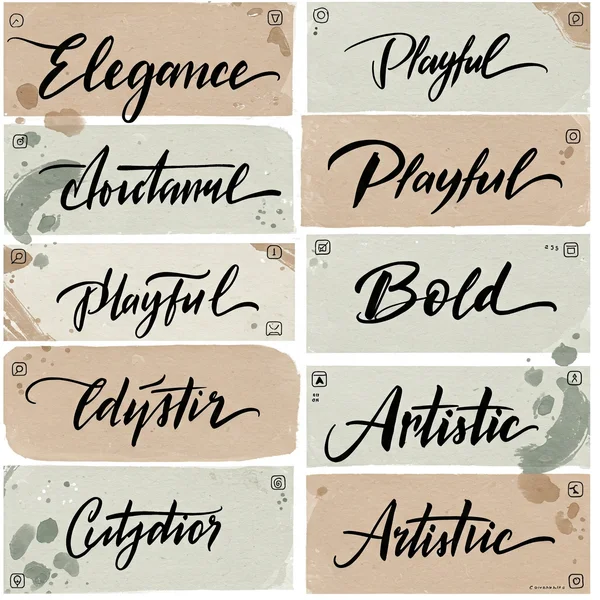
字體 1:「Elegancia Script」– 優雅的選擇
此字體體現了優雅和高貴,使其成為追求精緻外觀的 最佳草寫字體 之一。
主要特徵與氛圍
Elegancia Script 具有流暢的線條和經典的字母造型。它散發著永恆的優雅,非常適合想要展現優雅的品牌或個人。這是一種高度易讀的 Instagram 字體。
最適合:Instagram 個人簡介、Pinterest
非常適合製作誘人的 Instagram 個人簡介,為 Pinterest 圖片說明增添一抹優雅,或為需要精緻風格的引言圖表增添風味。
範例:「永恆之美」
字體 2:「Playful Swirl」– 俏皮的字體
使用這款活潑的字體為您的貼文增添一抹趣味和活力。
主要特徵與氛圍
Playful Swirl 的特點是其彈跳的基準線和異想天開的花飾。它現代、平易近人,非常適合輕鬆活潑的內容。如果您正在尋找 TikTok 字體,這是一個絕佳的選擇。
最適合:TikTok 字幕、有趣的 Facebook 貼文
將其用於引人入勝的 TikTok 影片文字、機智的 Facebook 更新或任何旨在有趣友好的社群媒體內容。
範例:「歡樂時光在前方!」
字體 3:「Statement Maker」– 大膽的聲明
當您需要您的文字引人注目時,這就是您應該選擇的字體。
主要特徵與氛圍
Statement Maker 是一種更為大膽、更具影響力的草寫字體。其強烈的筆觸和獨特的風格使其非常適合標題或強調關鍵訊息。這是一個很棒的 Twitter 字體 選項。
最適合:Twitter 焦點、YouTube 縮圖
非常適合讓推文中重要的文字脫穎而出,為 YouTube 影片縮圖文字增添風格,或用於號召性用語。
範例:「讓它引人注目!」
字體 4:「Minimalist Chic」– 極簡的魅力
對於那些欣賞低調優雅的人來說,這款字體是完美的搭配。
主要特徵與氛圍
Minimalist Chic 提供簡潔的線條和簡潔而優雅的草寫風格。它現代而精緻,又不失華麗。它是一種很受歡迎的 美學字體。
最適合:美學 Instagram 限時動態、部落格圖表
非常適合極簡主義 Instagram 限時動態文字、簡潔的部落格文章圖表或任何透過草寫風格點綴設計的內容。
範例:「簡約之美。」
字體 5:「Artisan Script」– 藝術的風格
使用這款獨特的仿手寫風格字體,釋放您內心的創意。
主要特徵與氛圍
Artisan Script 具有獨特且略有不規則的外觀,模仿真實的手寫字跡。它非常適合傳達創造力、獨創性和個人風格。一種真正 具有創造力的社群媒體字體。
最適合:創意作品集、藝術部落格
非常適合藝術家、設計師或以工藝為中心的企業,用於在社群媒體或部落格上展示其作品。
範例:「釋放創造力。」
在社群媒體上有效使用草寫字體的技巧
雖然 花俏的草寫字體 非常有效,但以下是一些技巧,可確保您有效地使用它們。 社群媒體字體的一些最佳實務是什麼?
優先考慮可讀性
選擇清晰易讀的字體,尤其是對於較長的文字。無論字體多麼漂亮,難以閱讀的字體都會讓您的觀眾感到沮喪。
與您的品牌保持一致
選擇符合您整體品牌識別和語氣的草寫字體。一致性有助於建立品牌知名度。
不要過度使用
策略性地使用草寫字體來強調或增加風格,而不是用於整段文字。過度使用會使您的內容看起來雜亂無章且難以閱讀。
在不同設備上測試
請記住,字體在不同設備和平台上的呈現方式略有不同。始終預覽您的貼文,以確保您選擇的 草寫字體 在任何地方看起來都很棒。
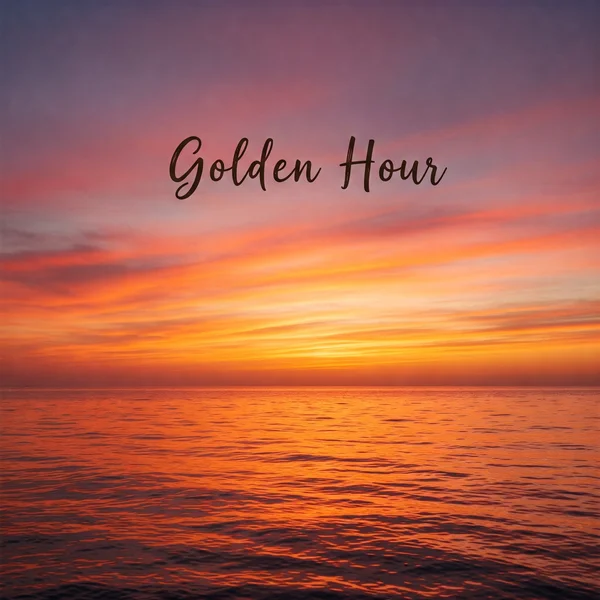
使用令人驚豔的草寫文字,轉變您的社群媒體!
使用正確的 草寫字體 可以大幅提升您的社群媒體形象,讓您的貼文更具吸引力,並更能反映您的獨特品牌。使用 草寫字體產生器,取得和使用這些引人注目的風格比以往任何時候都更容易。
社群媒體的草寫字體
以下是一些關於線上使用草寫字體的常見問題:
社群媒體中最受歡迎的草寫字體是什麼?
沒有單一的「最受歡迎」 草寫字體,因為趨勢會改變,個人喜好也會大相徑庭。但是,易讀、優雅的字體和略帶俏皮的現代字體往往對 社群媒體字體 具有廣泛的吸引力。關鍵是要找到最適合您的品牌和受眾的字體。
如何確保我的草寫文字在所有設備上都可讀?
為了最大限度地提高可讀性,請選擇更清晰、裝飾更少的草寫風格。如果可能的話,請在不同的設備上查看您的個人檔案/貼文來測試您選擇的字體。使用 花俏的草寫產生器 時,堅持使用更簡單的風格通常可以確保更好的跨平台相容性。